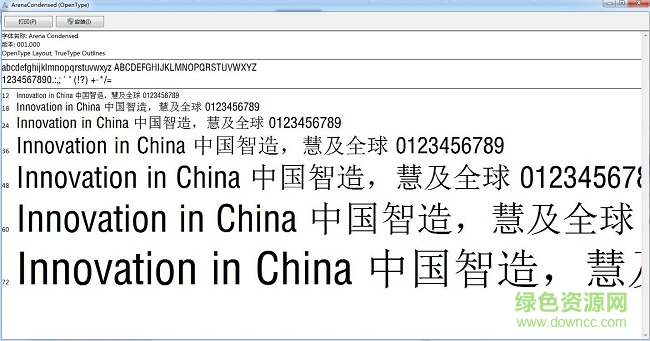
arenacondensed
arenacondensed字體是一款間距緊湊的無(wú)襯線字體,線條流暢,字形挺拔,風(fēng)格清新,符合現(xiàn)代特征,實(shí)用性強(qiáng),可以用于廣告、商品包裝、商標(biāo)等方面,感興趣的朋友快來(lái)下載吧!
字體風(fēng)格分類(lèi)
1.格調(diào)高雅,
2.簡(jiǎn)潔爽朗,
3.華麗高貴。
4.現(xiàn)代感強(qiáng),
5.具有重量感,
6.個(gè)性非常突出,
arenacondensed